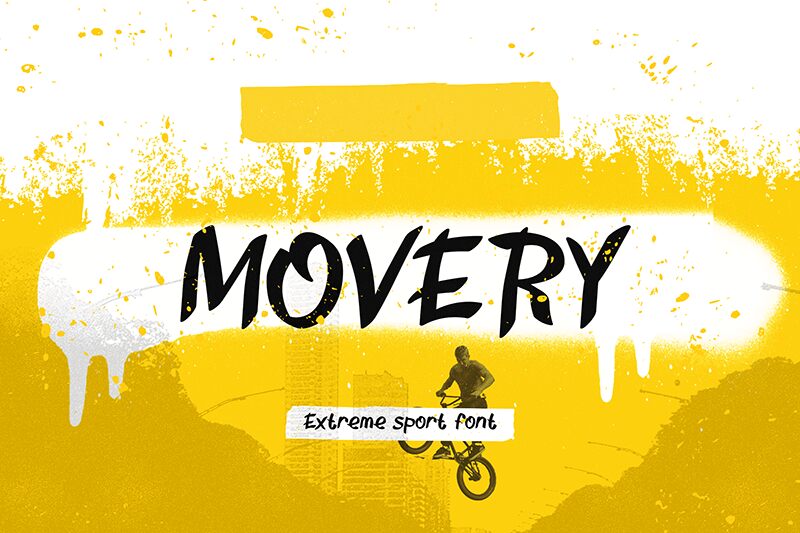
Movery de Skytroopas es una tipografía manuscrita tipo brush-script gratuita, con un ritmo ágil y un aire vintage que recuerda a los rótulos pintados a mano. Las letras alternan entre trazos gruesos y remates afilados, otorgándole un aspecto desenfadado y lleno de vitalidad, lejos de ser demasiado pulida o rígida.
Es ideal para carteles, branding de cafeterías, packaging, portadas de música y gráficos para redes sociales donde busques un toque artesanal. Como tipografía gratuita, Movery funciona de maravilla en titulares cortos, títulos de portada y logotipos, ya que sus trazos de pincel ancho y sus uniones puntiagudas aportan dinamismo incluso a las frases más breves.